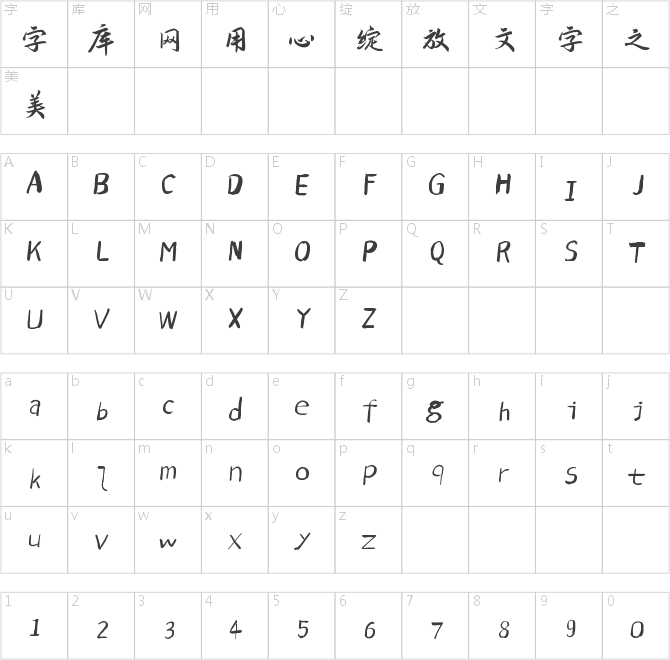
演示悠然小楷 詳情頁
字體名稱: 演示悠然小楷
演示悠然小楷
演示悠然小楷介紹
初看「演示悠然小楷」,可能并不覺得驚艷,再品,卻會發現透著質樸、率真的氣息。
正如尚在象牙塔中的作者本人,那是未經雕琢的拙樸書生氣。
這款「演示悠然小楷」的字稿作者——孟祥媛,生于1999年,是一位目前還在大學就讀的書法專業的學子